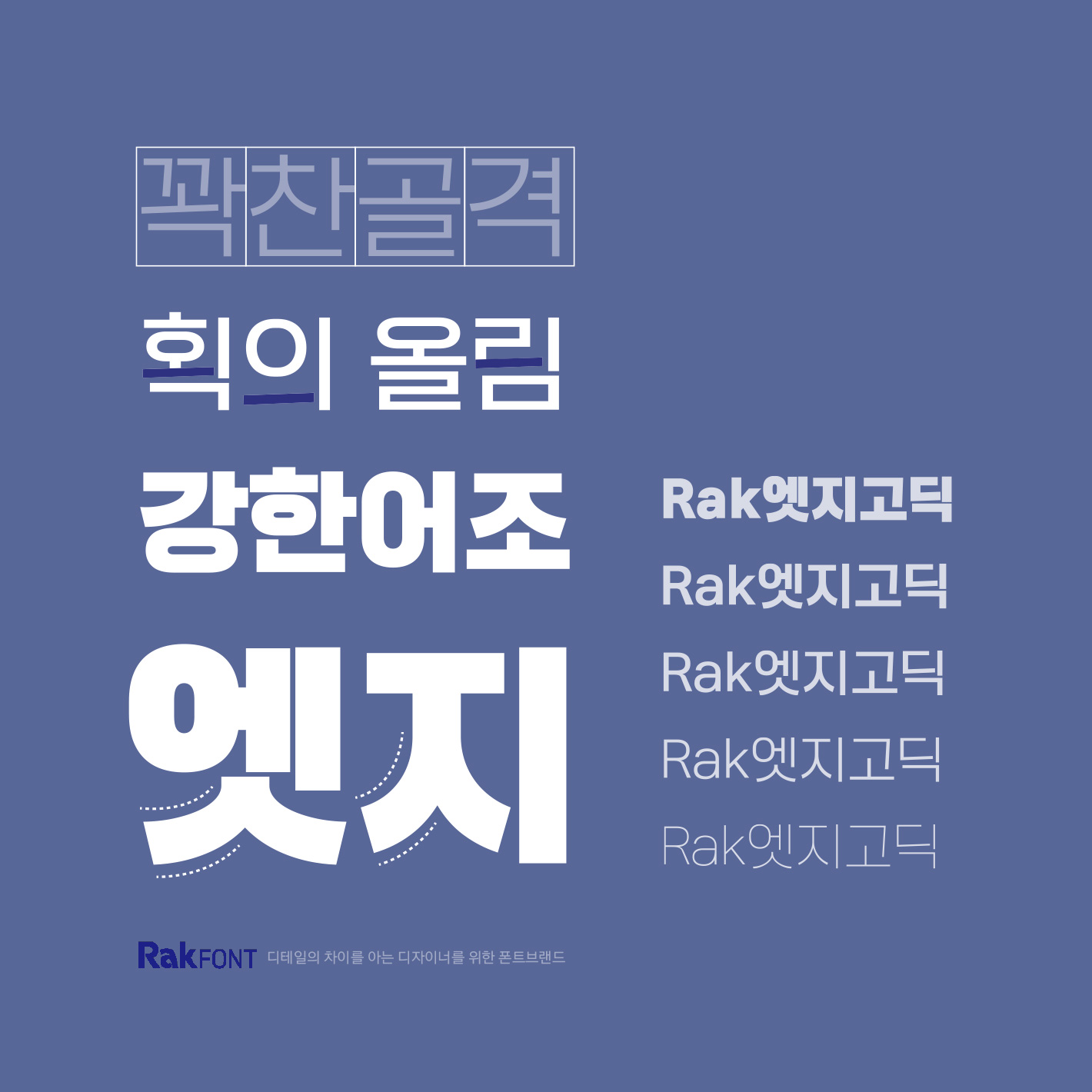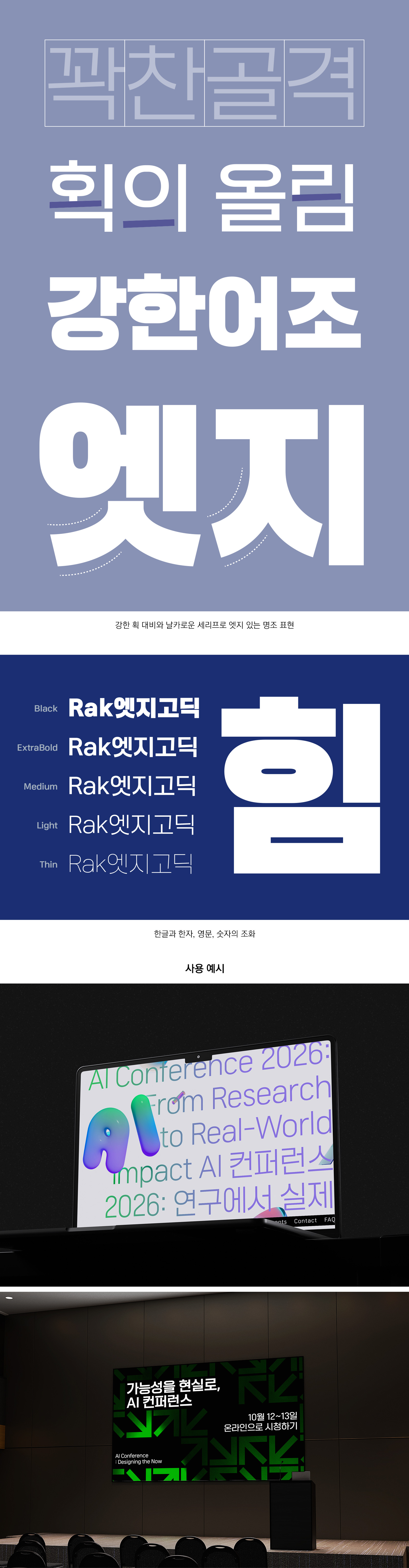
RakEdgeGo
5 Style - Black, ExtraBold, Medium, Light, Thin
RAK 엣지고딕은 엣지 시리즈 중 고딕계열로, 강한 어조와 높은 주목도가 필요한 환경을 위해 설계된 서체입니다. 획은 직선적으로 힘차게 상승하는 구조를 바탕으로 하고, ㄱ, ㅅ, ㅈ과 같이 텐션이 강한 자소에서는끝으로 갈수록 힘을 주어 날카롭고 단단한 인상을 강조했습니다. 총 5종으로 구성되어 다양한 사용 환경에서 활용도를 높였습니다.
FontFamily Rak엣지고딕 / RakEdgeGo
Design Park YongRak
Direction Park YongRak